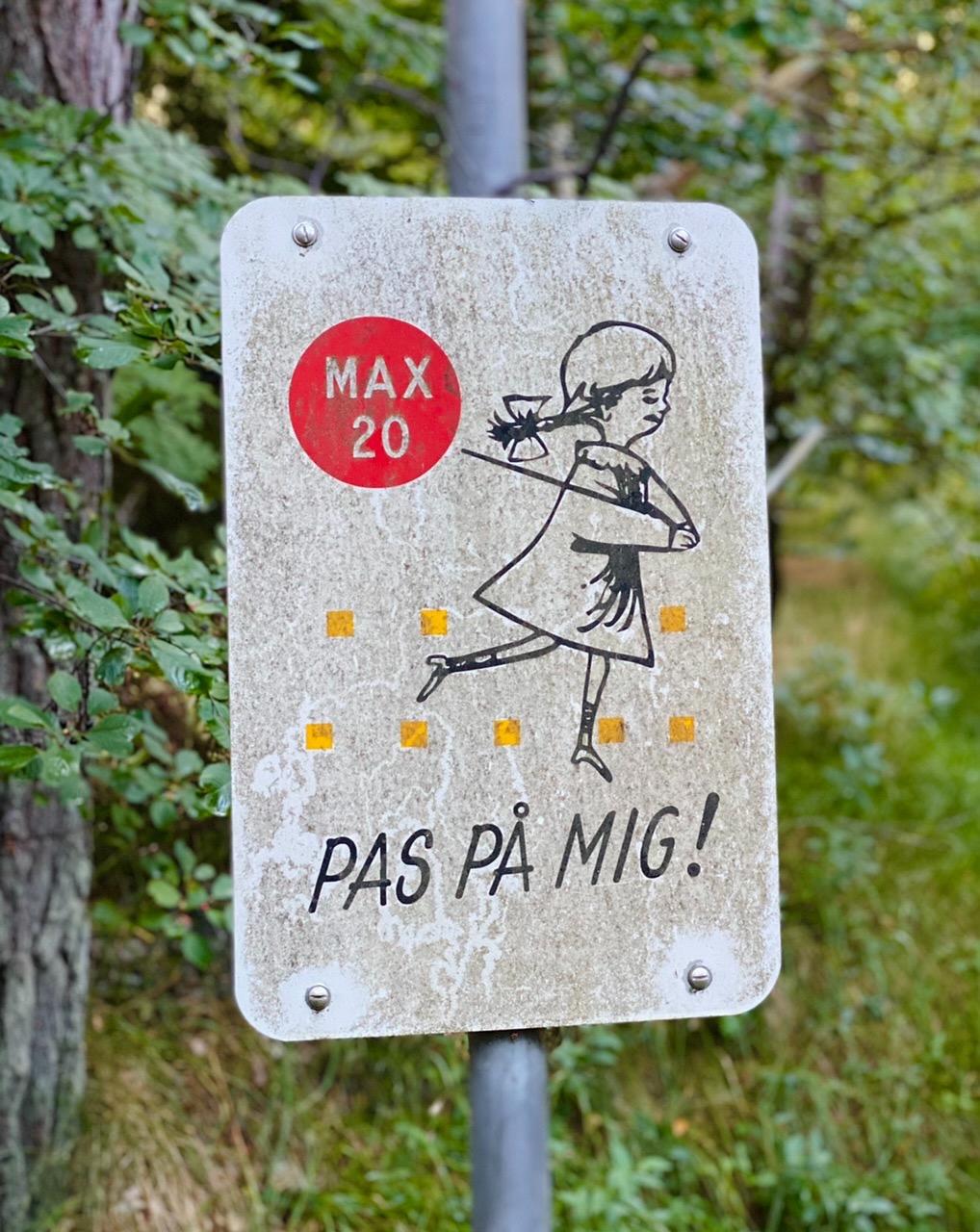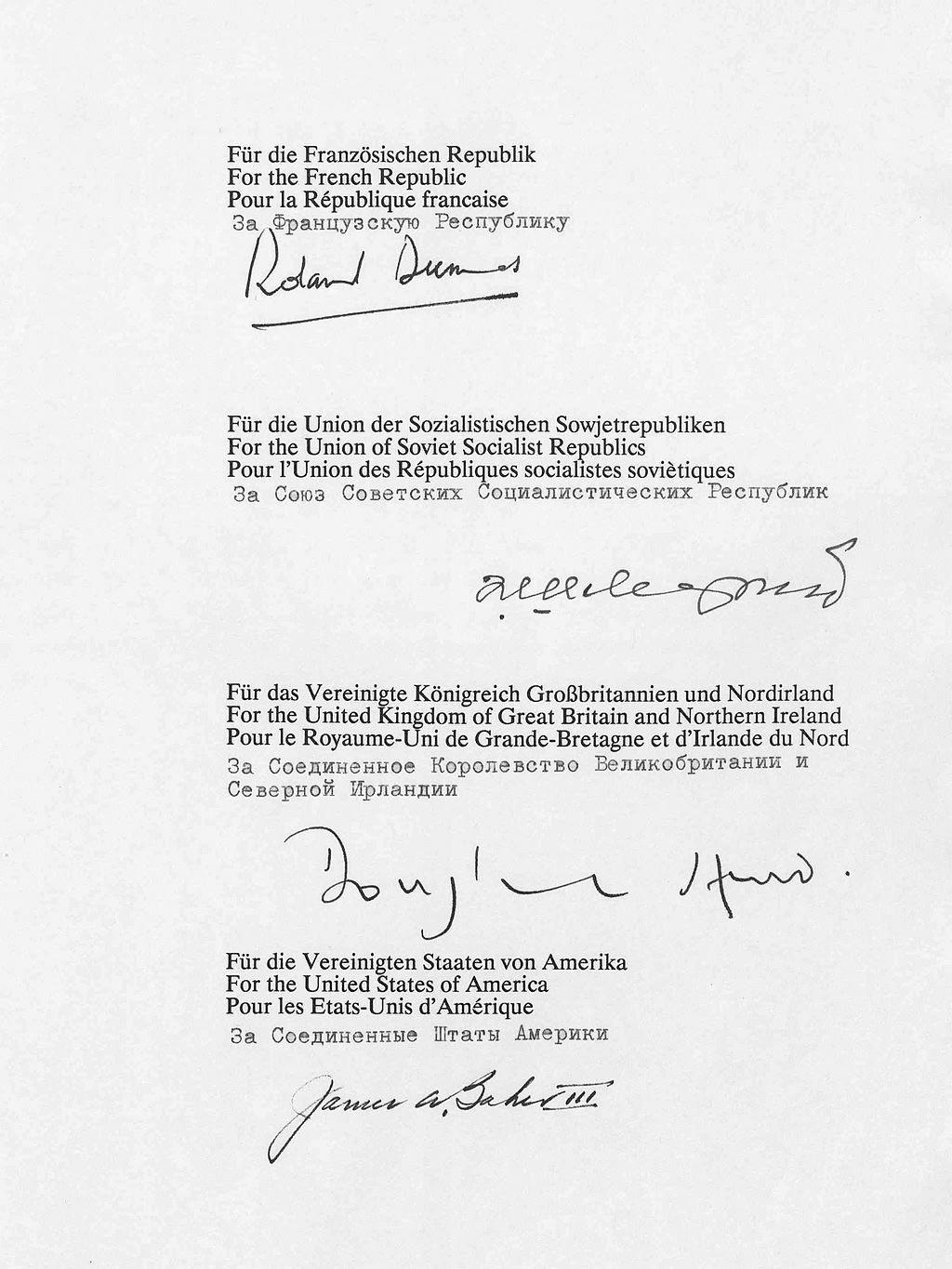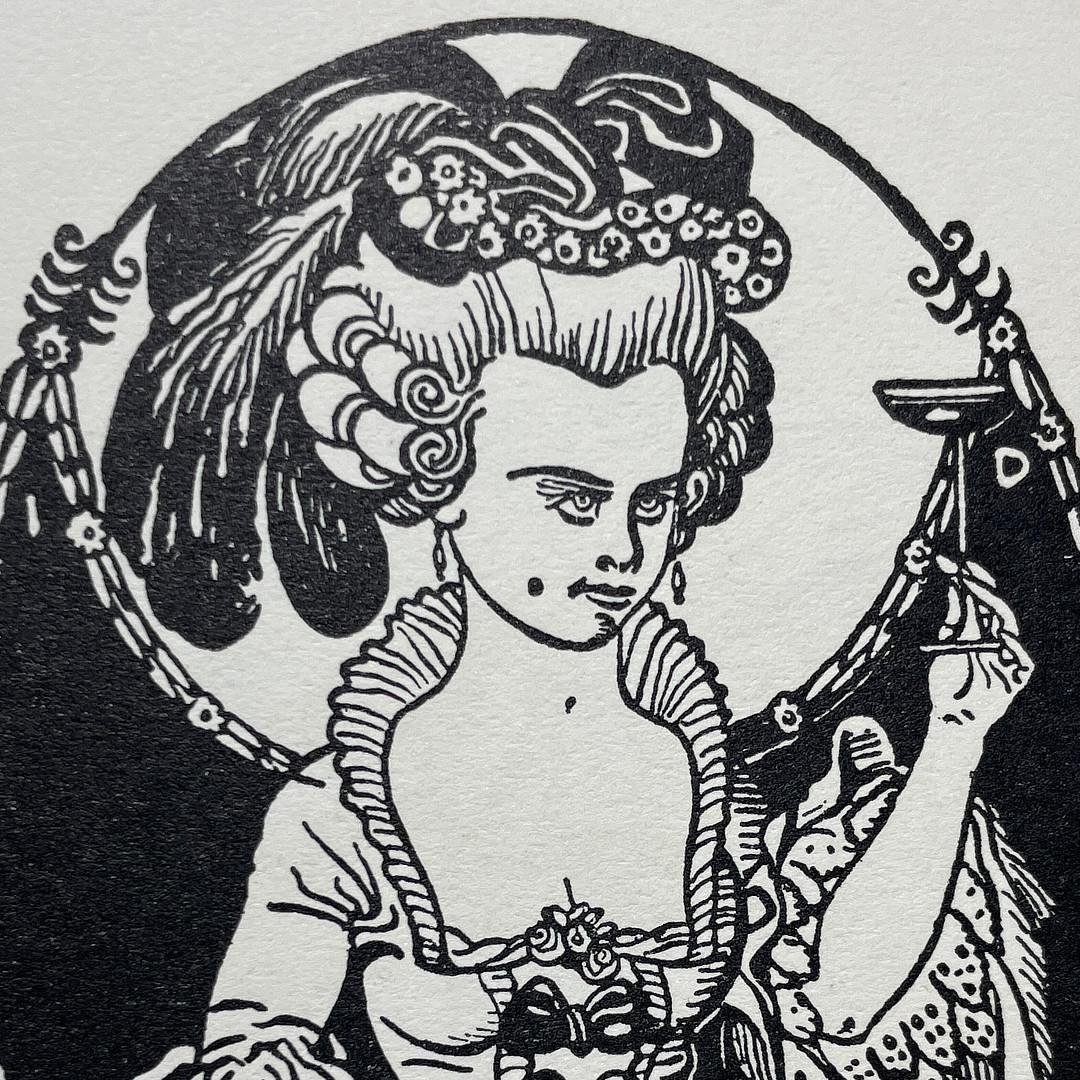
Nicht um vom Thema abzuschweifen, aber heute erhielt ich diese Probe mit Vignetten von Julius Diez, 1910 von der Bauer'schen Gießerei herausgegeben. Parallel mit dem Jugendstil gab es damals ein starkes Interesse an Holzschnitten im Stil Dürers. Herr Diez hat diesen Stil auf eine Reihe von Subjekten angewandt. Die von ihm gezeichneten Personen sind aber allesamt entweder blau, bekifft, oder sehr, sehr wütend 😄JuliusDiez02.jpg.8b936552a24d44b2c443b0a5decf7d89.jpgUmschlag.
Schick gemacht, und dreifarbig!JuliusDiez01.jpg.f7f783db11b4dd3e23850c1c7eed558b.jpgWell hello there, handsome...won't you buy a gal a drink?JuliusDiez06.jpg.4bc2c0d08fdf2f8274c9cc50ebb0b8ac.jpg
Could you fucking not?
JuliusDiez04.jpg.5f714dd9dbd09c442398dfe3065d78b5.jpg"Kein Problem, Frollein, ich halte ihnen gerne die Leiter"
JuliusDiez05.jpg.1907a18b6f0ff44849c7f05da2d3b1a0.jpg"Deine Zeit ist knapp bemessen. Sehr knapp." JuliusDiez07.jpg.5265e78ca30696c9bb871c308a771b56.jpg
LSD zeigt unterschiedliche Wirkungen.JuliusDiez09.jpg.0878b4a2cfa503d175125012eee0f040.jpg
Fleurop kommt auf die Sau.JuliusDiez10.jpg.ec1fe053f36e335aad931fd028835152.jpg
Galan: "Hier sind deine Scheißblumen, Margot!"
Putte: "Fix, 'n Eimer!"
200 Jahre Sand, Wind und Salzwasser − aber die Schrift lässt sich, zumindest teilweise, trotz der Erosion noch lesen.
Gesehen in Whitby in North Yorkshire.
Weil es mir heute wieder auf einem Hoody von Raf Simons aufgefallen ist…
Die Gestaltung des Labels für die Vinyl-Version von »Power, Corruption & Lies« von New Order.
Art-Direction: Peter Saville, 1983 (FACT 75)
Inspiration hierzu waren übrigens die Schriftscheiben der diatype-Fotosatzgeräte wie man in der Publikation »Peter Savile: Estate 1-127« erfahren kann.
»Wie, wir haben keine kyrillische Schrift? (…) Augenblick… Schewardnadse, habt ihr Sowjets eine Schreibmaschine dabei?«
Zieht das Mädchen das Schild im Schild als Luftballon hinter sich her? Clever.
Das Schild ist echt charmant. Aber ob es wirklich funktioniert? Die Wichtigkeit der Inhaltes (fahr nicht schnelle als 20) tritt gegenüber den anderen Elementen doch sehr zurück.
Kommt darauf an, wie gut so ein Schild gelernt und im (kollektiven) Gedächtnis verankert ist. Dann ist der Wiedererkennungseffekt wichtiger als die »Lesbarkeit«. Das Schild sieht jedenfalls nach »gibt’s schon länger« aus …
P.S.: Ob Banksy das Schild wohl auch kennt?
Ich weiß ehrlich gesagt nicht einmal ob das Schild offiziell ist. Gesehen habe ich es in einer waldigen 30er-Zone mit quasi unbefestigten Wegen und vereinzelten Ferienhäusern.